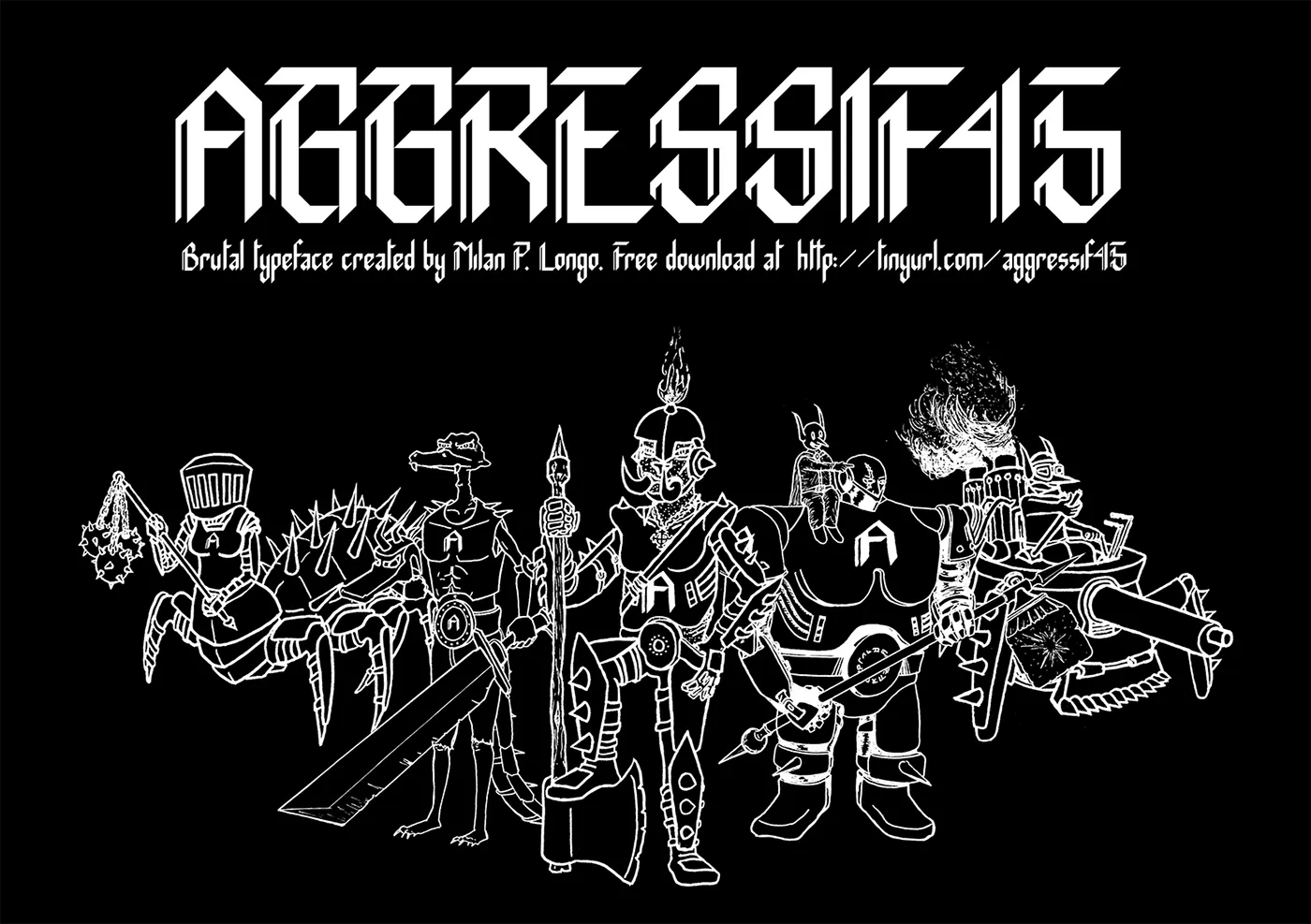
Aggressif 45 Typeface – Download Grátis
A Aggressif 45 Typeface é uma nova escolha para quem busca um estilo inconfundível que remonta aos tempos do Gothic Victoriano. Desenhada pelo Milan Longo, esta tipografia de cunho Blackletter oferece uma simplicidade e minimalismo impressionantes. Ela carrega os contornos robustos da tipografia tradicional dos anos 1800 sem perder a originalidade moderna. A Aggressif 45 é perfeita para quem procura uma fonte que se adapte a um leque amplo de produtos e projetos criativos. Seja em cartazes, selos, logotipos ou design de livros, ela traz o estilo único e poderoso que você precisa. Além disso, suas iniciais Aggressif45 podem ser usadas para transformar qualquer layout em um visual atraente. Se procura uma fonte moderna que honra o passado das letras gothicas Victorianas, a Agressif 45 pode ser exatamente a escolha certa. Ideal tanto para designers quanto para empresas atemporais, ela é uma opção versátil e poderosa no mundo digital atual.